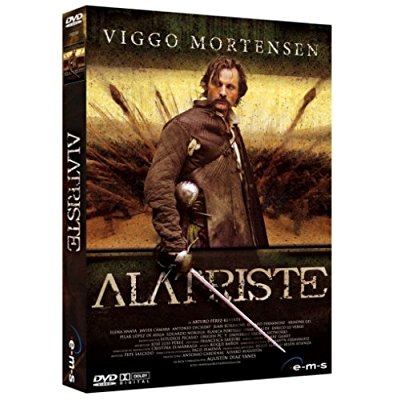
Falsch montiert
An die Rubbelbuchstaben, an alle Aluminium-Lettern, an alles im öffentlichen Raum, das auf dem Kopf steht – meist S, O oder H – habe ich mich gewöhnt. Aber bei einem Kinofilm?
Sowas wird doch hundertfach gesehen und geprüft, bevor es in Dreh/Druck geht! Überall steht das S im Logo auf dem Kopf :?
vielleicht ist es absicht und jemand sieht dahinter einen tieferen Sinn?
Unwahrscheinlich, da das S in Mortensen (soweit man das bei der Darstellungsgröße erkennen kann) richtig zu sein scheint und da sich ja besonders zwischen S und T mehr Hakelei und ein größeres Loch ergibt. Aber was will man von einem Volk erwarten, das grundsätzlich Buch- (und DVD-)rücken von oben nach unten liest?
Aber was will man von einem Volk erwarten, das grundsätzlich Buch- (und DVD-)rücken von oben nach unten liest?
naja, logischer istt das schon, wenn ein buch auf dem tisch liegt kann man dann es auch an der seiite gut lesen, nicht alle alte regeln sind wirklich praktisch, bei cd’s und platten stört das niemanden.
ich finde das verdrehte S auch nicht schlimm und es ist doch klar, dass es mit absicht gemacht ist, gefallen muss es nicht jedem, mir gefällt es auch nicht aber es ist kein drama.
vielleicht ist es absicht und jemand sieht dahinter einen tieferen Sinn?
Absicht ja, schließlich wär es viel mehr Aufwand, das V zu drehen als ein normales A zu tippen. Sinn sehe ich hier allerdings keinen (während das umgedrehte V mit dem Kreis darüber in STARGATE ja immerhin noch das kreisrunde Stargate reflektiert, auch wenn's ansonsten blöd aussieht).
Aber was will man von einem Volk erwarten, das grundsätzlich Buch- (und DVD-)rücken von oben nach unten liest?
naja, logischer istt das schon, wenn ein buch auf dem tisch liegt kann man dann es auch an der seiite gut lesen, nicht alle alte regeln sind wirklich praktisch, bei cd’s und platten stört das niemanden.
Heinrich hat Recht. Buchcover, die im Massenmarkt (Modernes Aniquariat) erscheinen, haben grundsätzlich stapelfähige Rücken. Nur so funktioniert's mit der Lesbarkeit im Erdgeschoss bei Thalia/Hugendubel/Mayersche. Die Buchrücken in den Regalen der Fachabteilungen möchte der Kunde aber nach wie vor mit nach links geneigtem Haupte lesen. Das nennt sich wohl Tradition.
vielleicht ist es absicht und jemand sieht dahinter einen tieferen Sinn?
Die Matrix. Ich bekomme schon wieder Schweißausbrüche. Das ist die Matrix. Ein weiteres Indiz, ich bin mir sicher.
Erst gestern sah ich eine Vorschau des Herrn Guido Knopp "Die Wehrmacht". Genau in dem Augenblick, in dem er "Hitler" sagte, las ich parallel in einem Angler-Buch das Wort "Heil". Eindeutig ein Zeichen. Ich bin dann gleich heute morgen zum Exorzisten und lasse nun drei Morgenandachten für für Ihn beten. Wen? Na, Guido Knopp natürlich... tssssss.... und warte auf weitere Vorzeichen.
Stammt vermutlich von einem typischen Grafiker. Selbst der Zwischenraum ist schlecht ausgeglichen.
Ich verstehe diese Diskussion nicht so ganz.
Es ist doch eindeutig, dass der Grafiker des DVD-Covers/Film-Plakates das »S« mit Absicht gedreht hat.
Schließlich geht man doch davon aus, dass er an einem elektronisch/digitalen Grafikprogramm dieses »Werk« erstellt hat.
Und da passiert es normalerweise nicht so häufig, dass ein Buchstabe plötzlich um 180 grad gedreht wird,
wenn man es nicht mir Absicht tut. Schließlich hat er ja auch mit Absicht das »A« modifiziert.
Es sei denn, er hat einen dieser Trash-Freefonts verwendet, wo das »S« auf dem Kopf steht ... freaky :roll:
Nee ... die »A«s und »T«s sind verschieden zerkratzt. (vielleicht aber auch ein Trash-Versal-Font
mit zwei verschiedenen Kratzer in der Typo pro Buchstabe ... Spekulationen, Spekulationen)
Wartet mal auf das neue Logo des Süddeutsche Verlags, dass ich heute als einer der ersten zu Gesicht bekommen habe! :roll:
Heute hat mir mein Buchhändler in einem ganz anderen Zusammenhang etwas erzählt, und dabei ging es um Lautschrift. Deshalb weiß ich jetzt, daß diese Form des A ohne waagrechten Strich zum internationalen phonetischen Alphabet gehört (http://www.omniglot.com/writing/ipa.htm, siehe die Tabelle mit den "vowels", und dort "Open-mid" und "back"). Vielleicht liegt der Sinn also einfach nur darin, die gewünschte Aussprache zu verdeutlichen? (Ich fürchte allerdings, daß es im gezeigten Beispiel nur ein optischer Gag sein soll.)
Stammt vermutlich von einem typischen Grafiker. Selbst der Zwischenraum ist schlecht ausgeglichen.
Was ist denn ein typischer Graiker? Jemand der gerne Buchstaben verdreht? Und wirklich schlecht ausgeglichen sehen ganz andere Dinge aus.
... und dabei ging es um Lautschrift. Deshalb weiß ich jetzt, daß diese Form des A ohne waagrechten Strich zum internationalen phonetischen Alphabet gehört (http://www.omniglot.com/writing/ipa.htm, siehe die Tabelle mit den "vowels", und dort "Open-mid" und "back"). Vielleicht liegt der Sinn also einfach nur darin, die gewünschte Aussprache zu verdeutlichen? (Ich fürchte allerdings, daß es im gezeigten Beispiel nur ein optischer Gag sein soll.)
Stammt vermutlich von einem typischen Grafiker. Selbst der Zwischenraum ist schlecht ausgeglichen.
Was ist denn ein typischer Graiker? Jemand der gerne Buchstaben verdreht? Und wirklich schlecht ausgeglichen sehen ganz andere Dinge aus.
Jemand der sich nicht sonderlich mit typografie auseinander setzt sondern frei gestaltet. Nur bedeutet ''freie gestaltung'' nicht immer gute Kunst.
Und darum schrieb ich auch nur schlecht und nicht ''wirklich schlecht''.